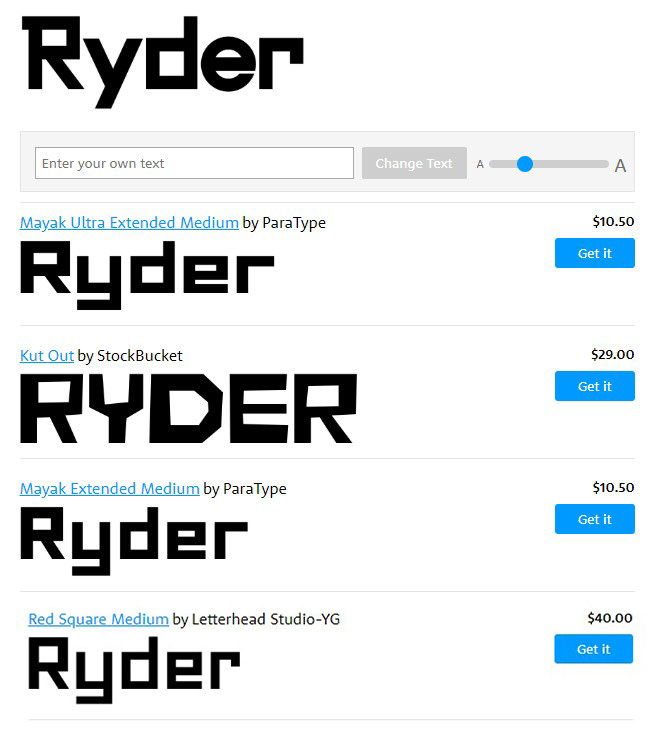
Подскажите шрифт?⁠⁠
Подскажите пожалуйста шрифт, срочно нужно?
Подскажите шрифт?
Нет такого шрифта, скорее всего просто название нарисовали. Видите, буквы разные, это не свойственно шрифтам. Несколько стилей в одном.
Вот подобные посмотрите, может быть из них что вам подойдет.